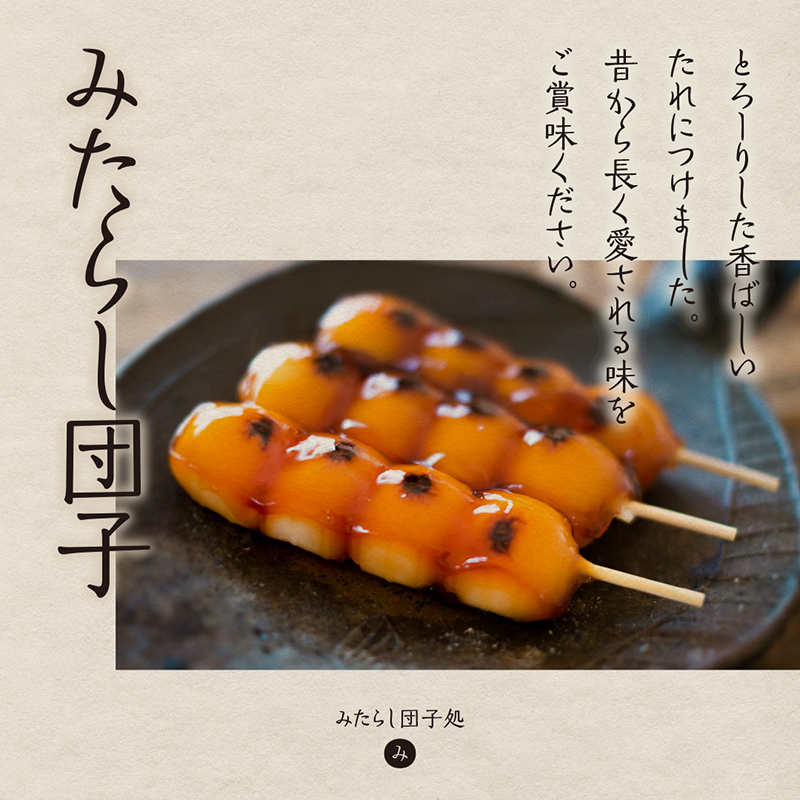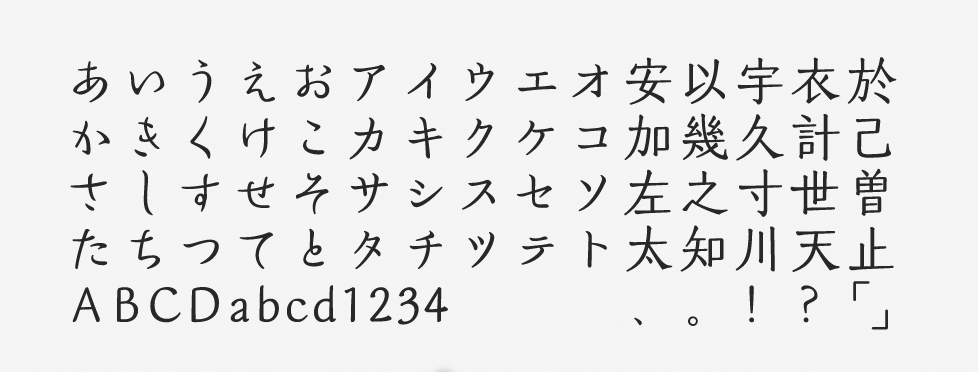
「みちくさ」について
みちくさは2017年にリリースされたフォントです。OpenType機能を使うことで、縦組みの際に文字がつながる「連綿体」や、豊富な代替字形を呼び出すことができます。やや古風・伝統的なイメージもありますが、可読性は高くて “今っぽい” という印象もある使い勝手の良いフォントです。
「みちくさ」の特徴
ふところを絞った骨格と、やわらかくて現代的なエレメントで構成された明朝体風のデザインフォントです。全体的にはすっきりとした印象で、和モダンな印象を表現したい場合にも適しています。
OpenType機能で利用できる「連綿体」は、いわゆる「続け字」で、文字の並びによって形が変化します。この機能を活用する場合には、テキスト次第で見え方が変わるため、クライアント・編集サイドとの連携が特に重要であると言えるでしょう。
今のところ、縦書きでの仮名の連綿が使用できるフォントはまだ少ないので貴重です。良いアクセントになり、目を引くことができます。和食系のデザインをする際には、まず候補に入れておきたいフォントです。
タイトル・見出し、書籍、雑誌、パンフレット、商品パッケージ、ラベル、チラシ、POP、看板、挨拶状